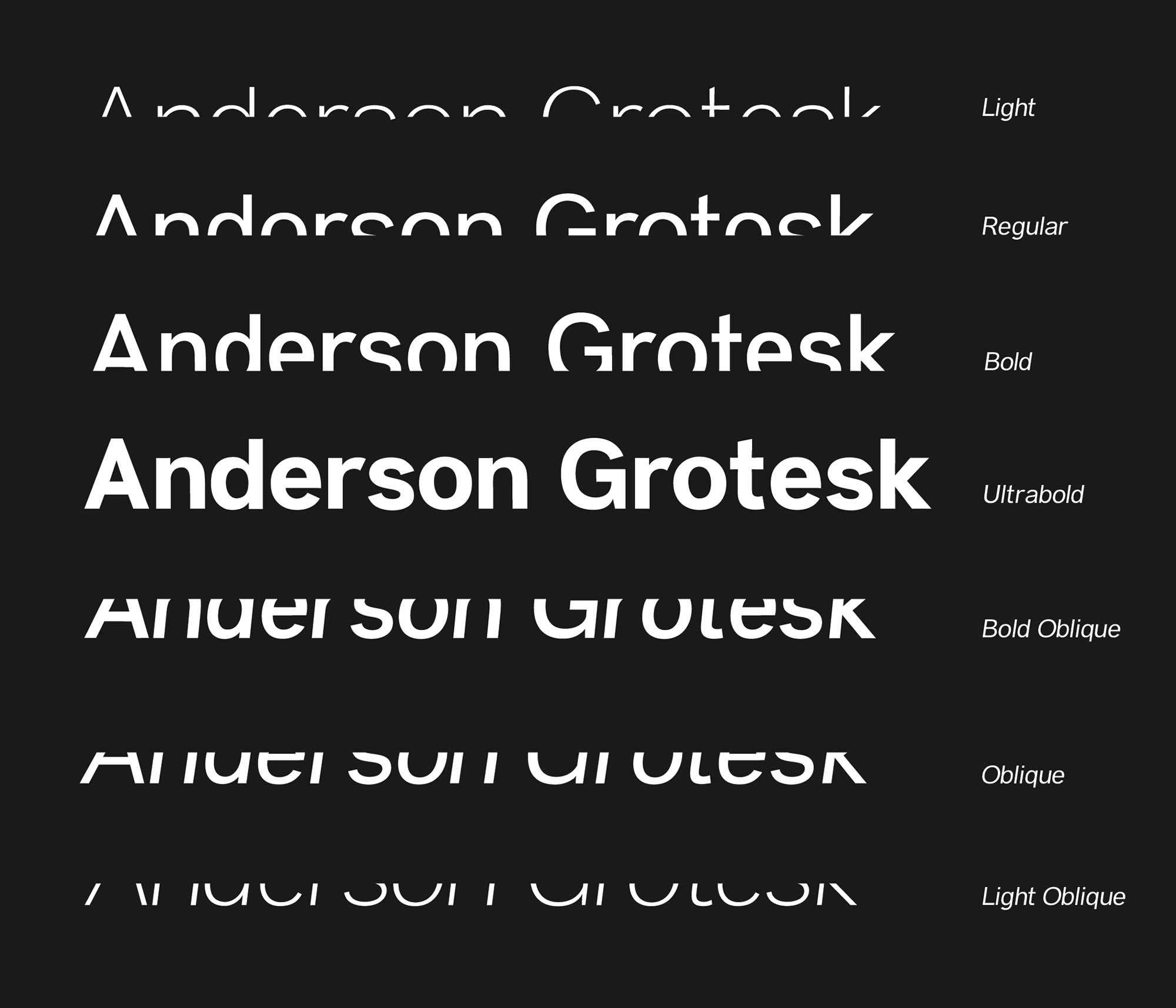
Anderson Grotesk Font
Olhem para este tiposet minimalista e moderno. Este font sans serif possui linhas limpas e simples, disponível em várias estilos e pesos de forma que vai de um peso regular até um tipo obliquo bold. Este é um ótimo recurso para uma marca de produto ou embalagem que você deseja usar universalmente. Transforme suas cartas de noivado em algo ultra-sleek e estiloso usando uma das muitas opções incluídas neste tiposet, ou personalize anúncios formais para um impacto ainda maior. Este font é uma excelente escolha para quem deseja dar um toque elegante e contemporâneo a sua identidade visual.